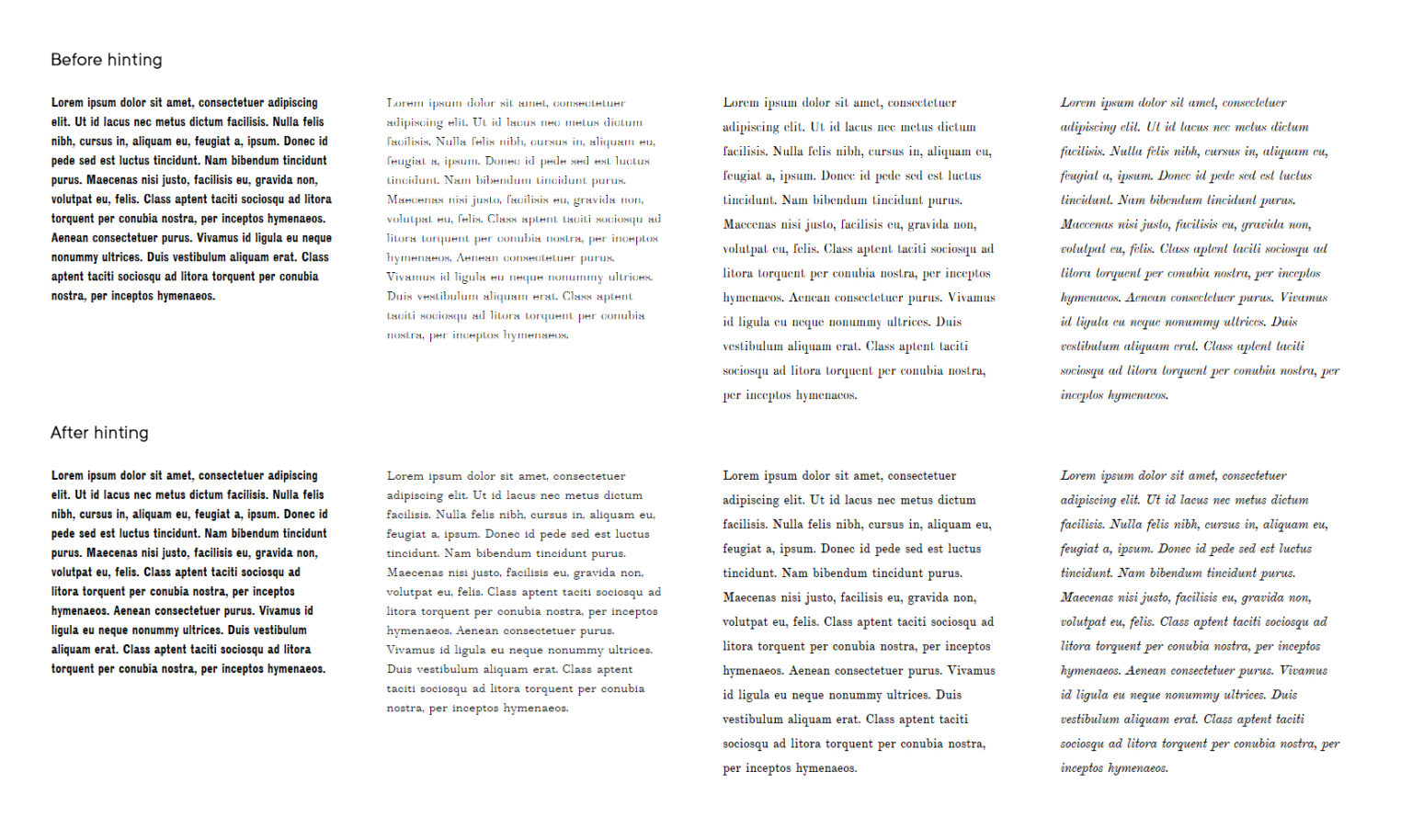
Хинтинг шрифта
Хинтинг улучшает внешний вид текста и его читабельность при низком разрешении экрана или мелком размере шрифта.
TrueType хинтинг (или инструктирование) — подсказки, которые накладываются при масштабировании на контуры знаков шрифта и лучшим образом отражают изначально заложенные дизайнером формы на любом размере, устройстве, разрешении и программном обеспечении.
Мы производим TrueType хинтинг как статичных отдельных начертаний, так и вариативных шрифтов. Используем Visual TrueType и ряд собственных технических подпрограмм для оптимизации работы над хинтингом.
Хинтинг шрифта
Четыре ключевые задачи, которые решает хинтинг:
1. Обеспечивает контраст — хинтинг позволяет вернуть шрифту контраст, задуманный дизайнером;
2. Повышает читаемость — при небольших размерах текста именно хинтинг борется за читаемость знаков;
3. Поддерживает спейсинг — хинтинг не позволяет буквам слипаться между собой и контролирует расстояние между буквами так, как это задумал автор;
4. Отвечает за ровную строку — хинтинг позволяет во всех размерах шрифта буквам держаться внутри своей строки и не выпрыгивать из нее.
Хинтинг